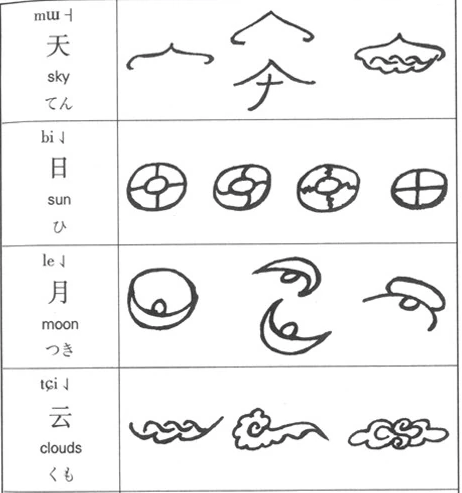
东巴文是一种居于西藏东部及云南省北部的少数民族纳西族所使用的兼备表意和表音成分的图画象形文字,当地把东巴文称为“司究路究”,意思为写在木头、石头上的印记,属于文字起源的早期形态,但亦能完整纪录典藏。东巴文源于纳西族的宗教典籍兼百科全书的《东巴经》。由于这种文字由东巴(智者)所掌握,故称东巴文。
东巴文创始于唐代,至今已有一千多年的历史。随着纳西族社会的发展和民族文化的相互影响,在明末清初,从东巴象形文字演变发展而来的还有一种标音文字,称“哥巴文”。“哥巴”是弟子的意思,“哥巴文”的意思是东巴什罗后代弟子创造的文字,“哥巴文”是对东巴文的改造和发展。